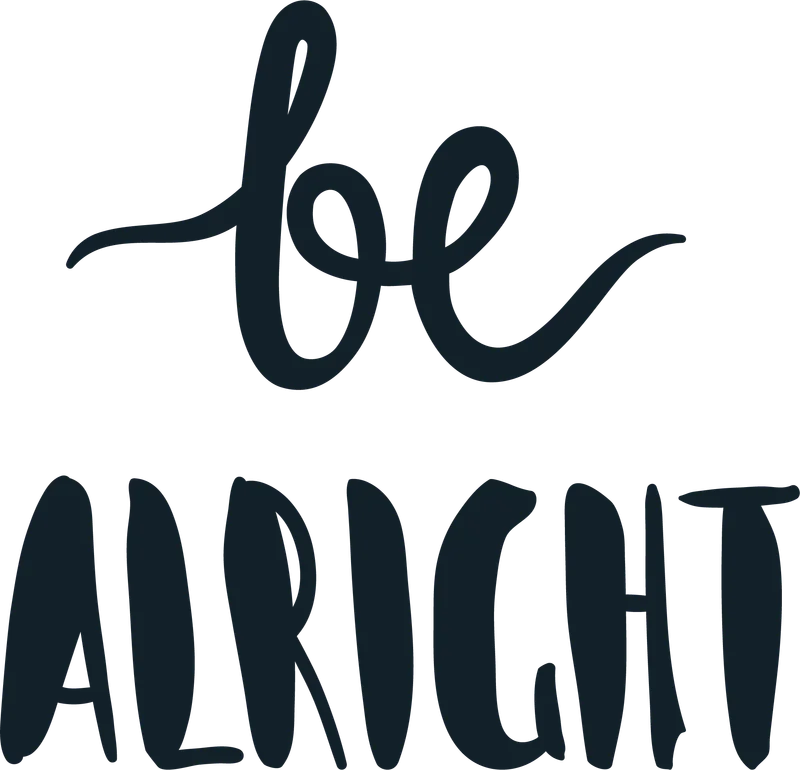
Thông điệp "Be Alright" font chữ thư pháp
Thông điệp "Be Alright" font chữ thư pháp — Thiết kế typography độc đáo với thông điệp "Be Alright" ý nghĩa, phù hợp in lên áo thun, túi tote, cốc và nhiều vật phẩm khác. Phong cách hiện đại, truyền cảm hứng.